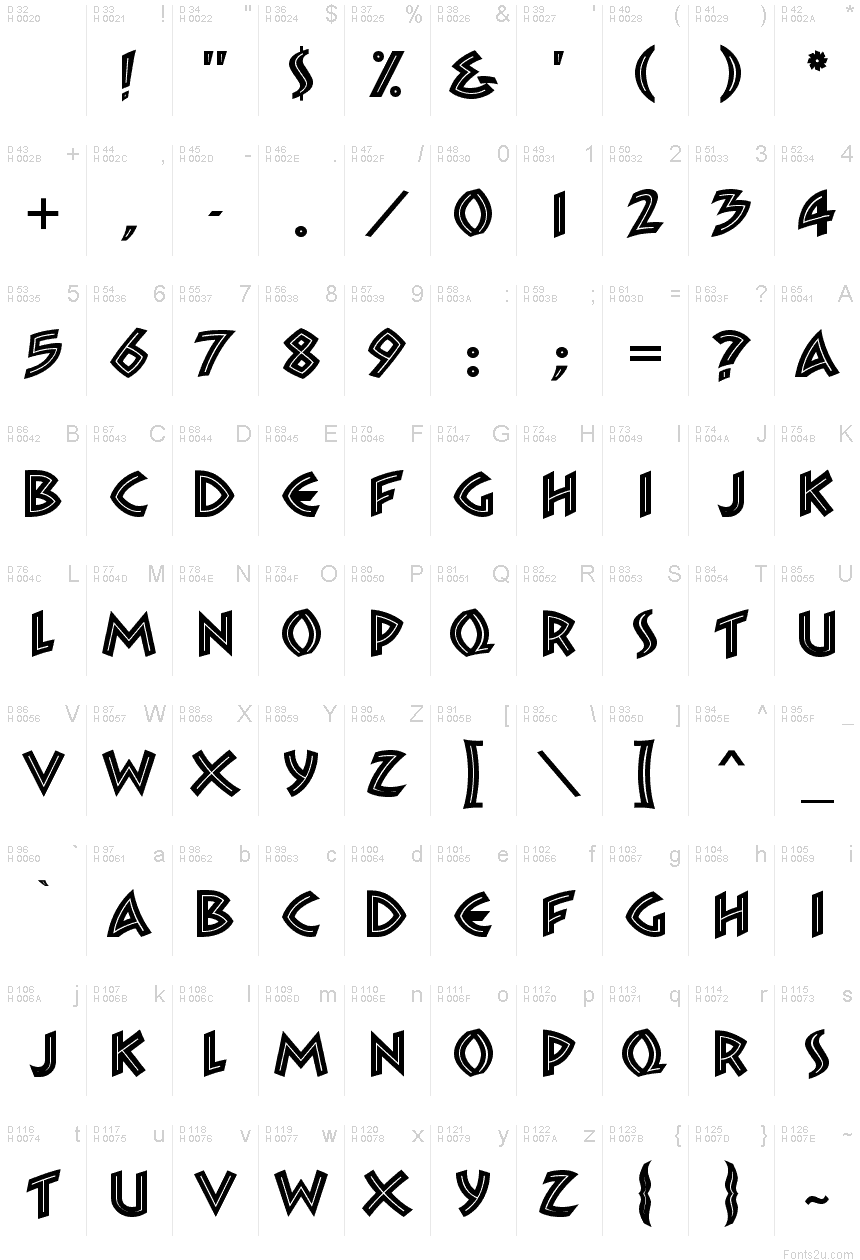
Zambesi MN od Mecanorma International to darmowy, dekoracyjny krój pisma typu display o wyrazistym, „rzeźbionym” charakterze, przypominającym wycięcia w ciemnym drewnie lub ślady grubego markera. Masywne, czarne formy oraz ostre, nachylone sylwetki liter nadają całości dynamiki, a jasne wewnętrzne kontury sprawiają, że znaki pozostają czytelne nawet z większej odległości. Krój ten emanuje energią ręcznie malowanych plakatów festiwalowych i murali, wyróżniając się nieco dzikim, nieszablonowym rytmem.
Zastosowanie Zambesi MN sprawia, że nagłówki natychmiast przykuwają uwagę. Ten darmowy font świetnie sprawdzi się na plakatach, ulotkach imprezowych, w logotypach gier, na opakowaniach produktów czy w oprawie graficznej wydarzeń dla dzieci. Dzięki otwartym formom wewnętrznym litery prezentują się dobrze zarówno w druku, jak i na ekranie, zwłaszcza w większych rozmiarach, gdzie w pełni widać ich rzeźbiony styl. W mniejszych blokach tekstu warto zestawić go z czystym, geometrycznym krojem bezszeryfowym, aby zachować równowagę i przejrzystość kompozycji.